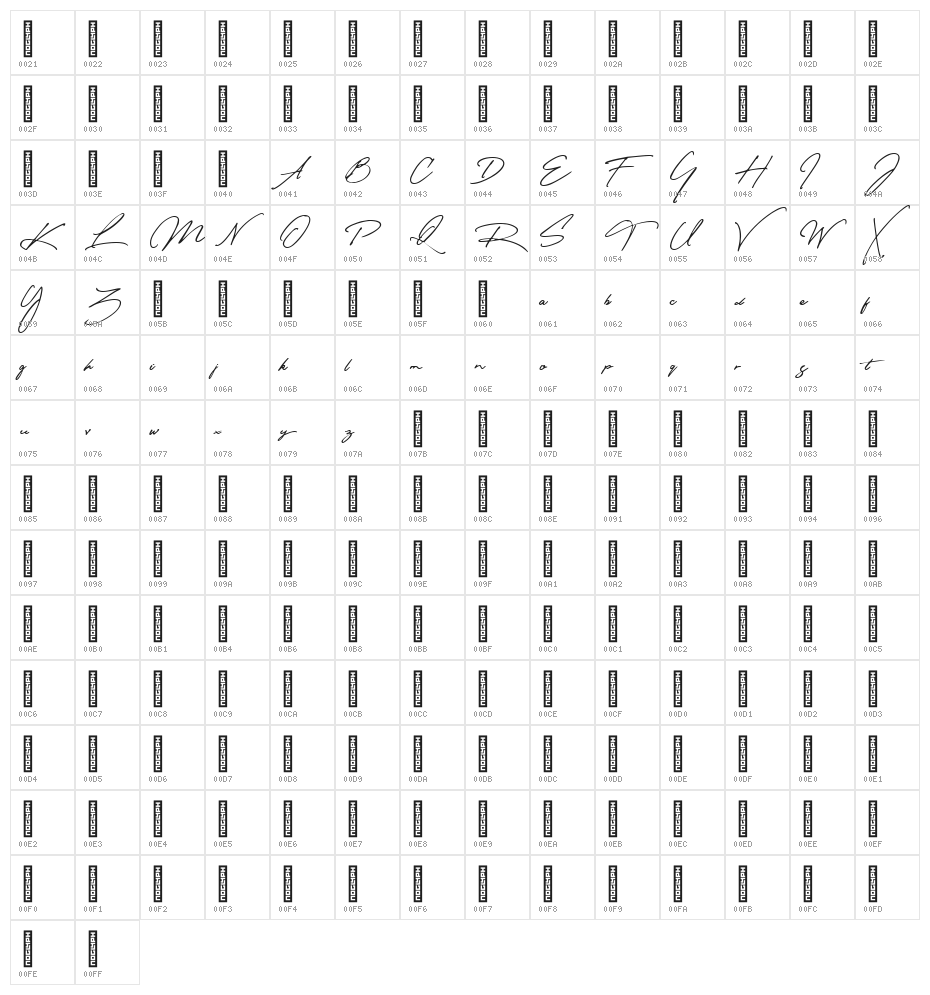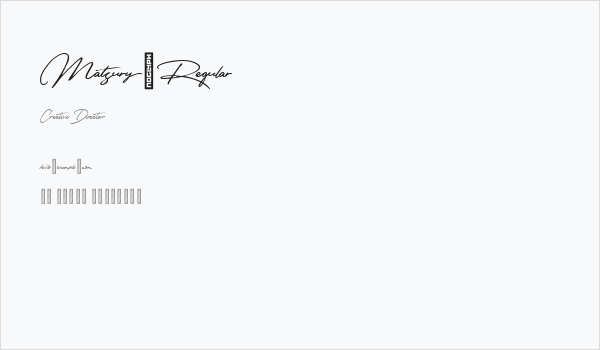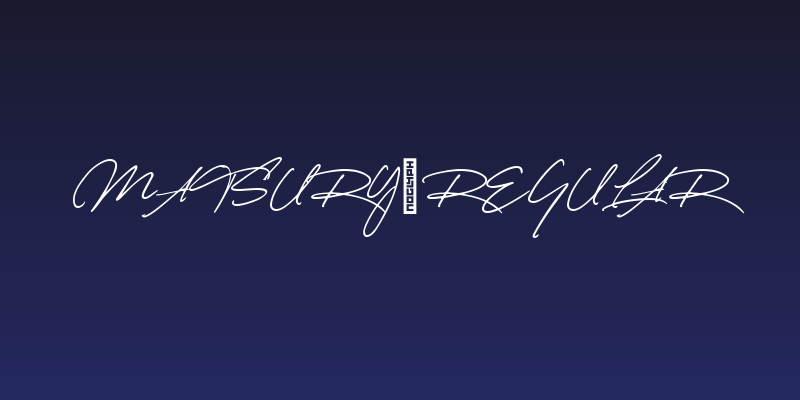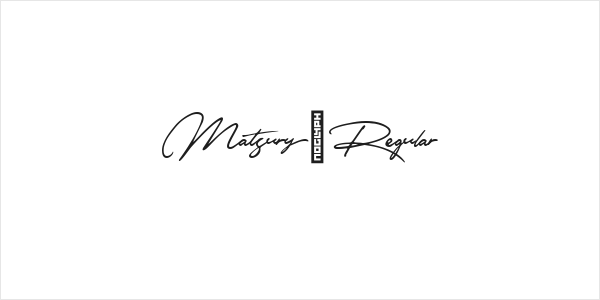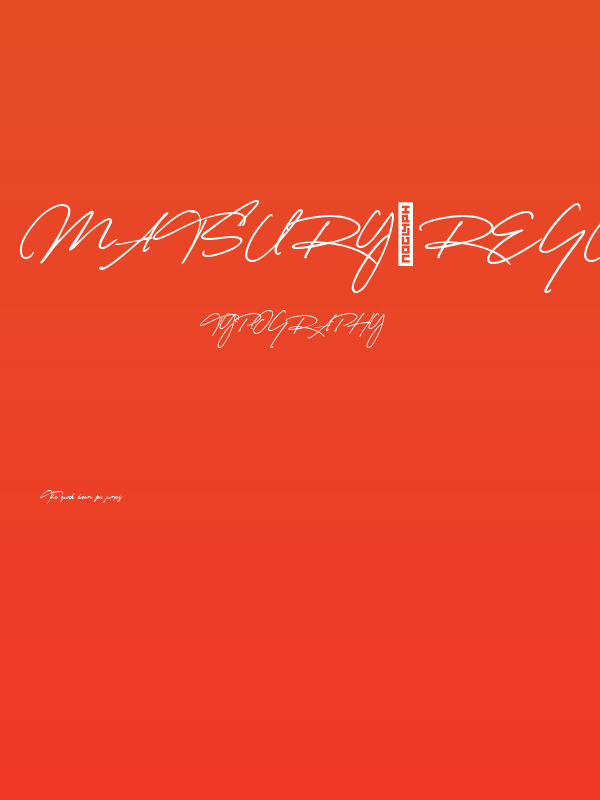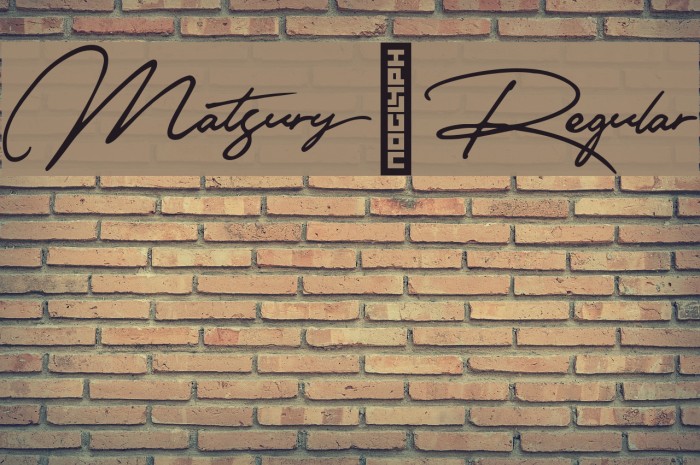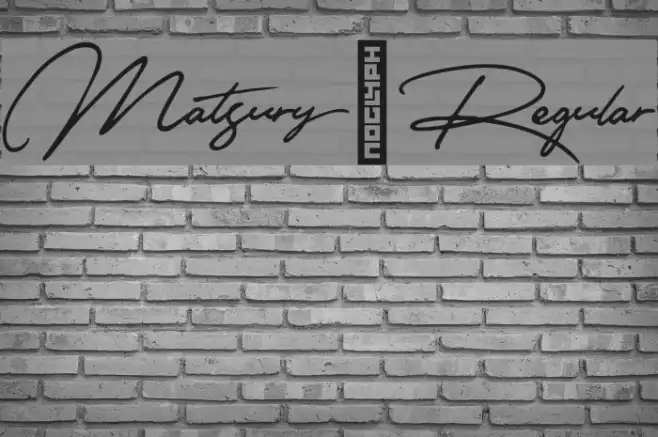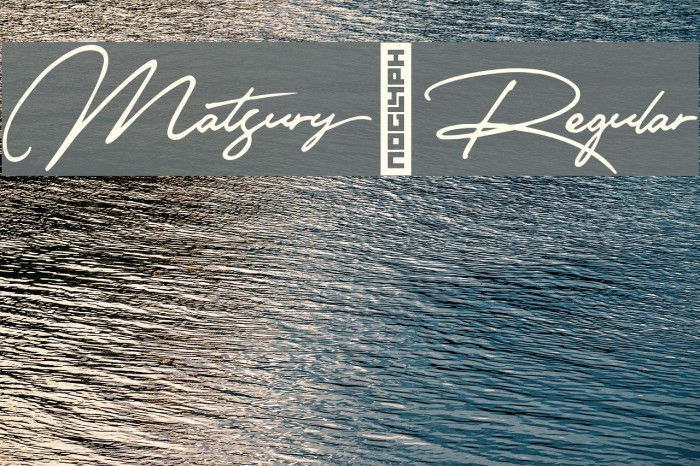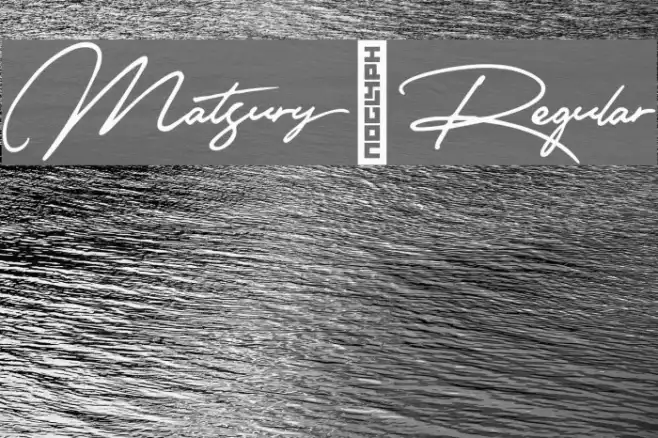
Matsury-Regular Font
| Familia de fuentes | Matsury |
| Estilo general | Elegant |
| Caso de uso | Logos, Invitations, Personal Branding |
| Proyectos propuestos | Ideal for wedding invitations, personal branding, and elegant stationery design. |